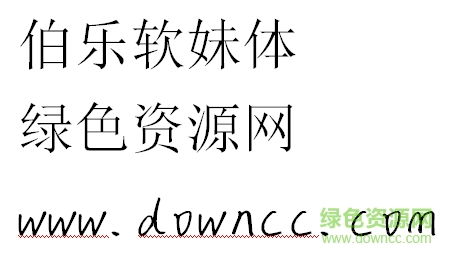
伯樂軟妹體是伯樂字體中花香體的加粗補全版,字體帶著軟妹的萌萌特點,充滿了可愛乖巧的氣息,喜歡的朋友快來綠色資源網(wǎng)免費下載吧!
伯樂軟妹體前身是伯樂話箱體,經(jīng)過補全和加粗后,稱為伯樂軟妹體,也叫做伯樂俏皮體,字體活潑可愛,像一個嬌氣的小姑娘,讓你的藝術(shù)設(shè)計、廣告創(chuàng)作別有一番風味。